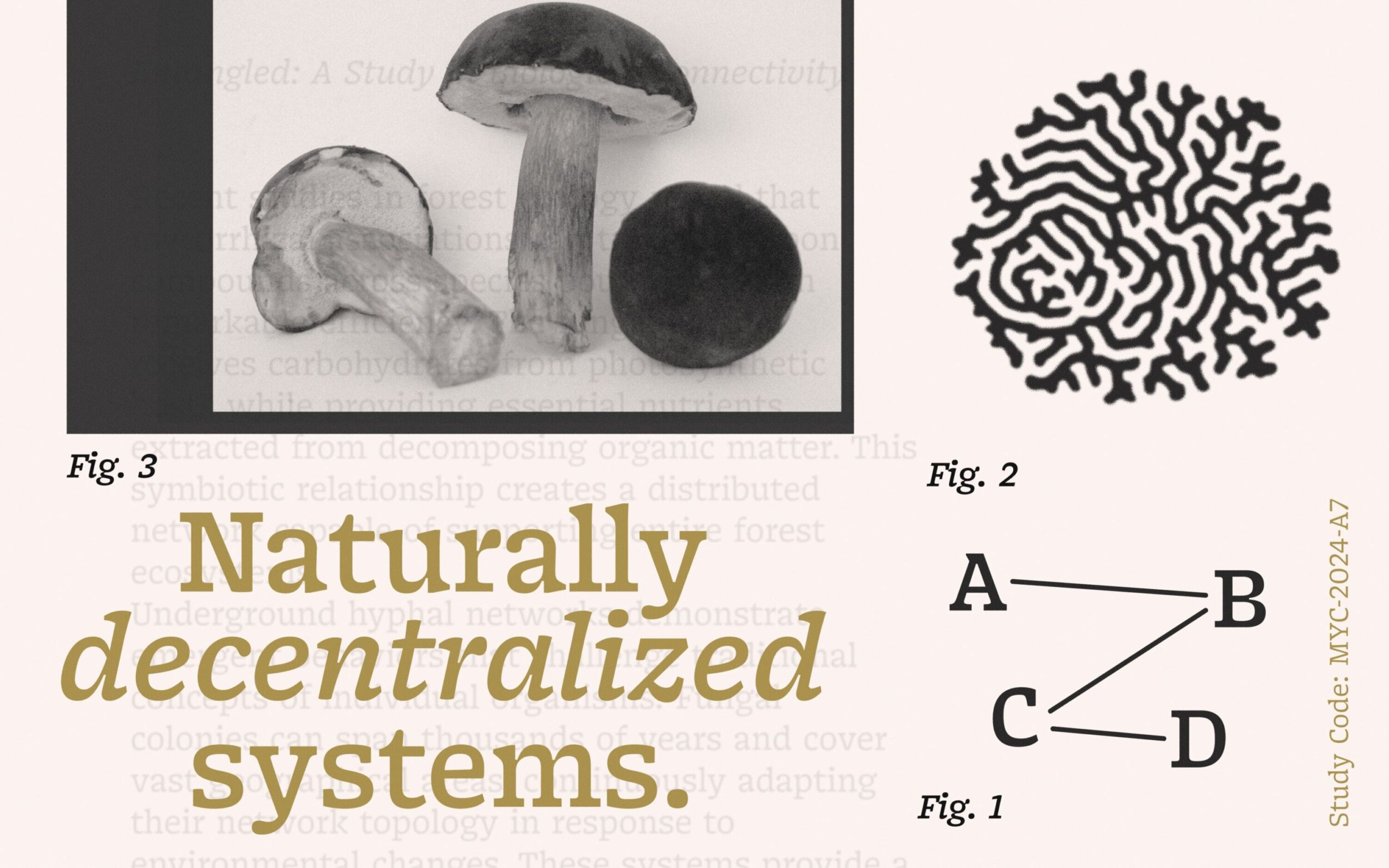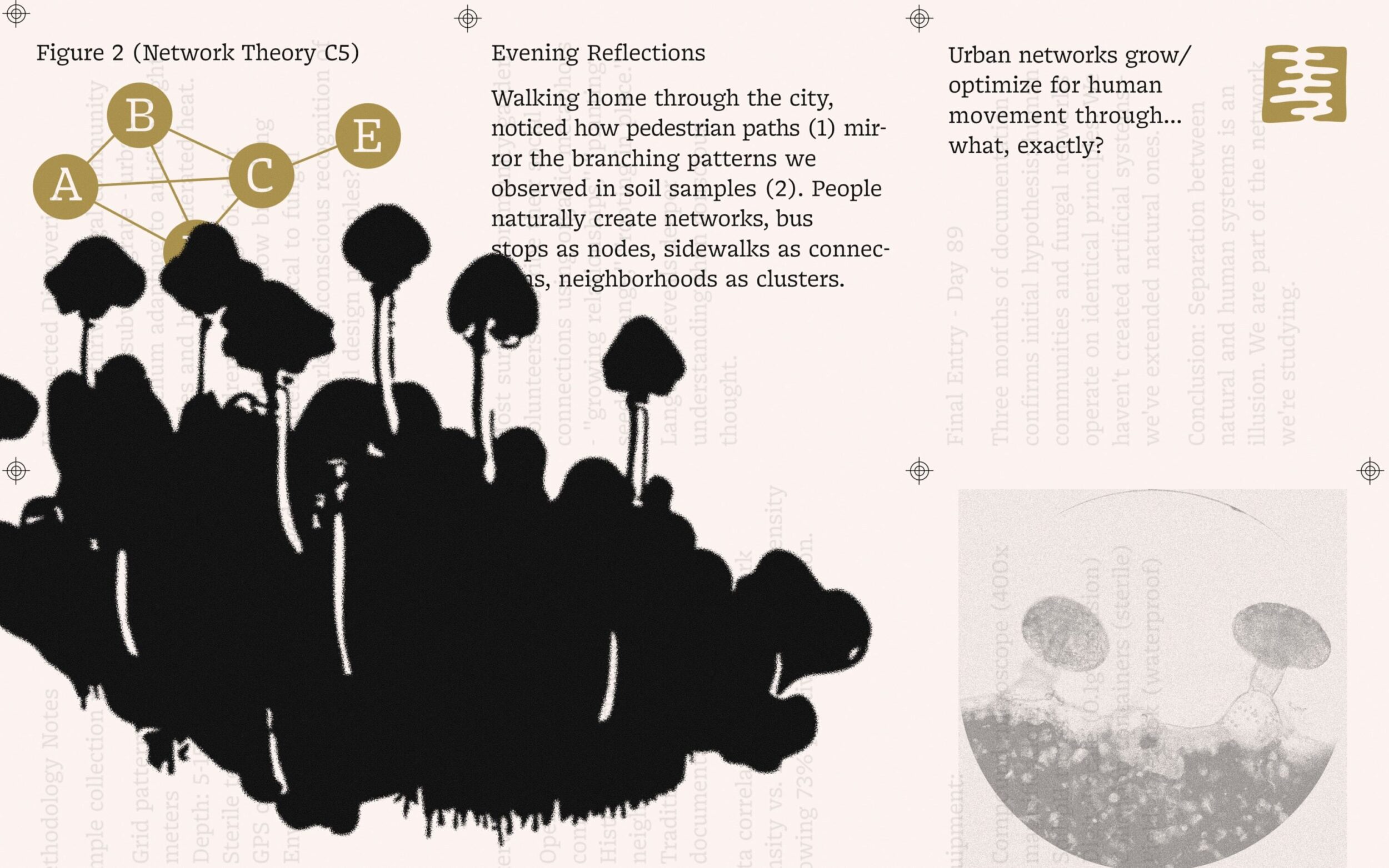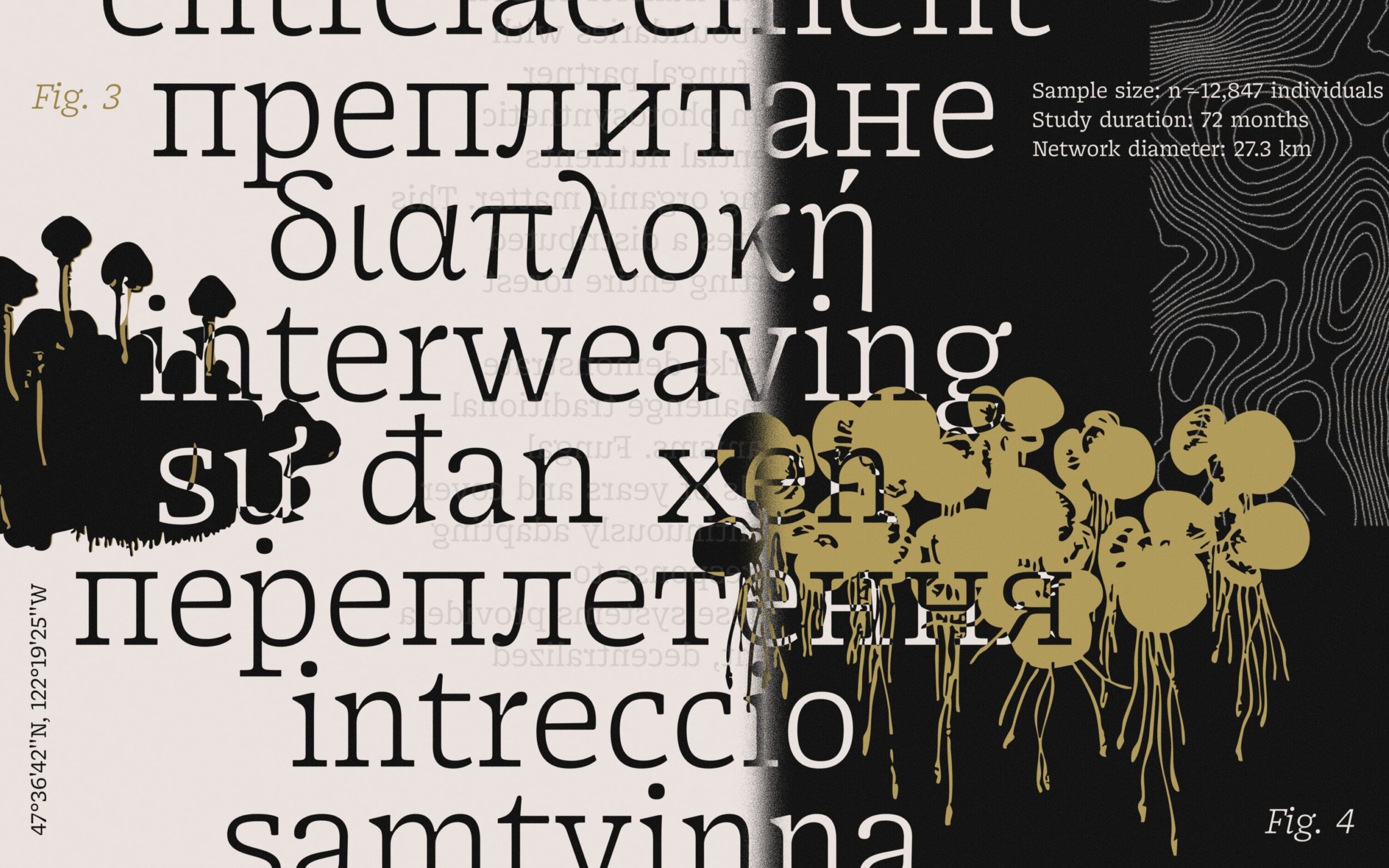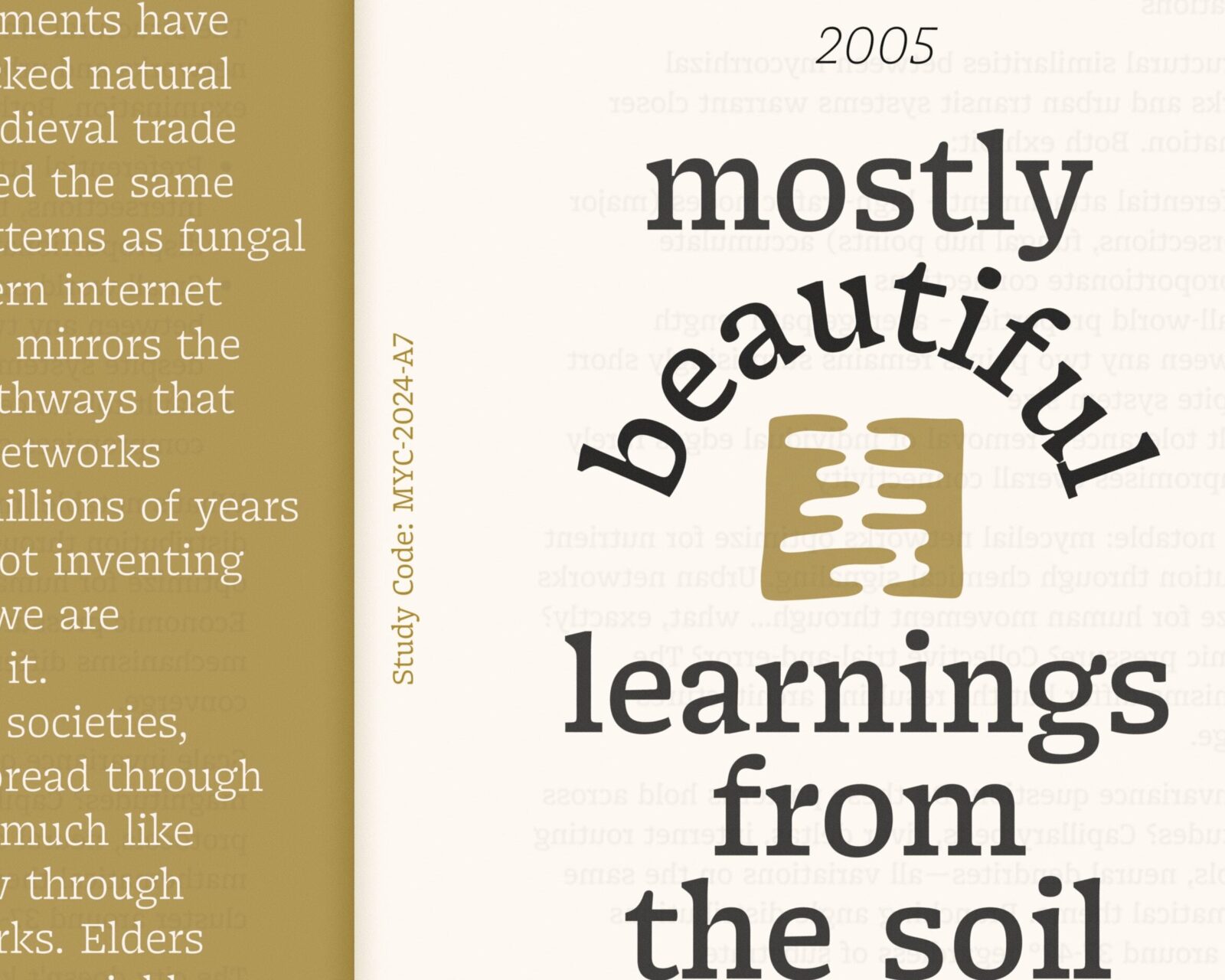
Gregory Text
😃 Verleiht jedem Wort Charme.
Gregory Text ist dein stabiler Buddy für Lesetexte und darüber hinaus. Diese bodenständige und herzliche Buchschrift zeichnet sich durch charmante, kleine Eigenheiten aus: markant im Detail, pragmatisch im Ganzen.
Mit moderatem Strichkontrast und ungewöhnlichen Formen interpretiert Gregory Text die Ästhetik historischer Slab-Serifs aus dem Bleisatz neu und passt sie an die heutigen Proportionen an. Das Ergebnis ist eine zeitgenössische Schrift, die warme Akzente, handgemachte Details und auffällige Ink-Traps der nüchternen Geometrie vorzieht. Ihr liebenswürdiger Charakter wird durch klobige, minimal gekehlte Serifen und eckig-ovale Punzen betont. Das robuste Genre der Familie wird aber durch die filigranen, leichten Schriftgewichte ausgeglichen.
Damit ihre Formen im Micro-Text klar erkennbar sind, nutzt Gregory Text die M-Formula von W. A. Dwiggins mit betonten Kanten, verstärkten Details und überzeichneten Binnenformen. Daraus ergibt sich ihre besondere Optik und ausgezeichnete Lesbarkeit: Gregory Text kann komplexe Texte mit sympathischem Charme abbilden. Für kleine Schriftgrößen entwickelt, entfaltet sie ihre Wirkung jedoch auch in großen Formaten, denn ihre kräftigen Details stechen in Überschriften wirksam hervor.
Die passende Kursive ist geprägt von beherzt kantig geschwungenen Formen, die eine strapazierfähige und zugleich lebendige Textur erzeugen: Sie verstärken den Reiz für Micro-Texte und barocke Top-Heaviness. Gregorys solide Konstruktion, ihre großzügige x-Höhe und markanten Kursiven kreieren eine funktionale Schrift mit einladendem Charakter – eine zuverlässige Wahl für seriöse wie auch informelle Typografie: Egal was du schreibst, Gregory verleiht den Worten Charme.
Mit Griechisch und Kyrillisch, exklusiv entworfen von Muttersprachlern, unterstützt Gregory Text mehr als 270 Sprachen, einschließlich Vietnamesisch. Sorgfältig produziert und ausgestattet mit einer Reihe von OpenType-Features für anspruchsvolle Typografie – einschließlich einer Auswahl an Ziffernsätzen, zurückhaltend rhythmischen Mediävalziffern, sprachspezifischen Varianten und feinen Symbolen und Emojis.
Verbunden im Herzen, anders im Detail: Gregory Poster und Gregory Grotesk harmonieren ideal mit der Gregory Text. Alle drei versprühen eine ähnliche positive Energie und überzeugen mit freundlichem Enthusiasmus, setzen mit ihrer eigenwilligen, voneinander unabhängigen Gestaltung jedoch verschiedene Akzente.